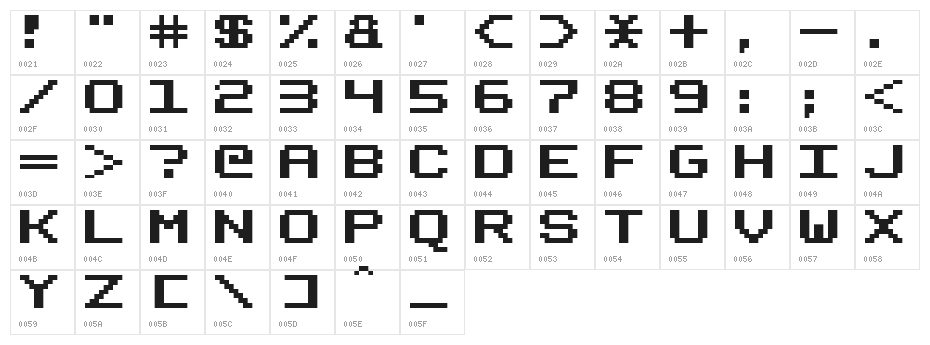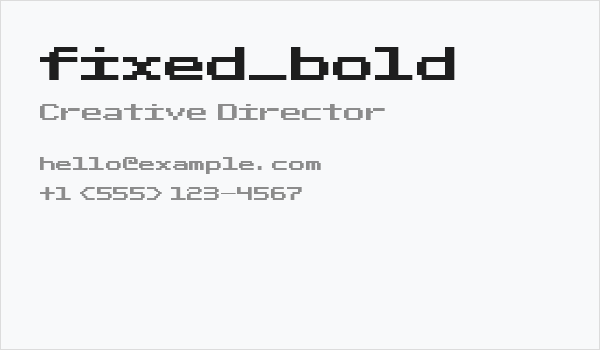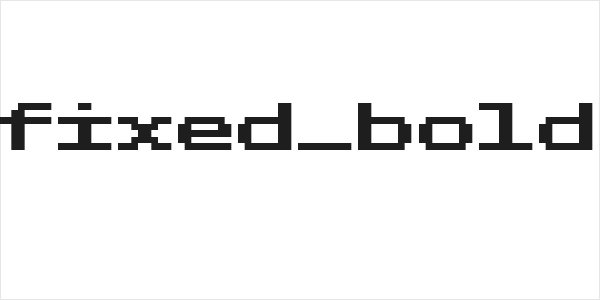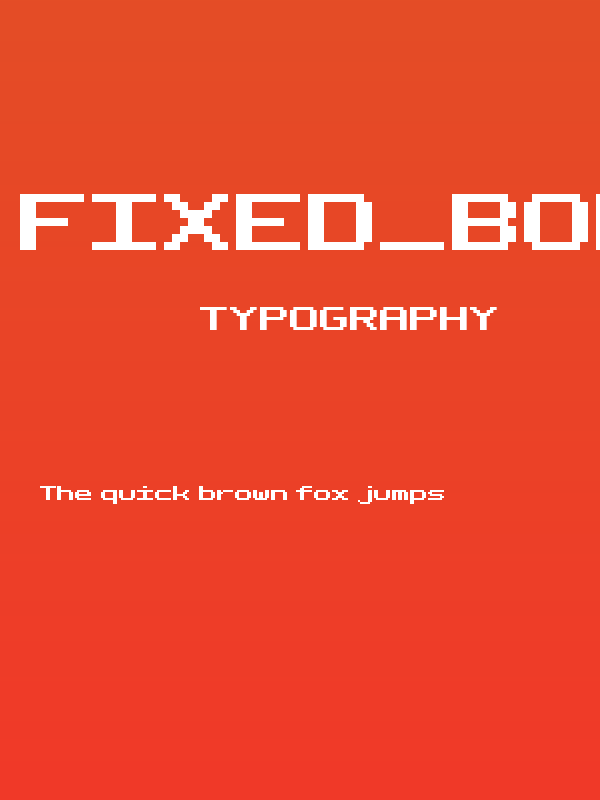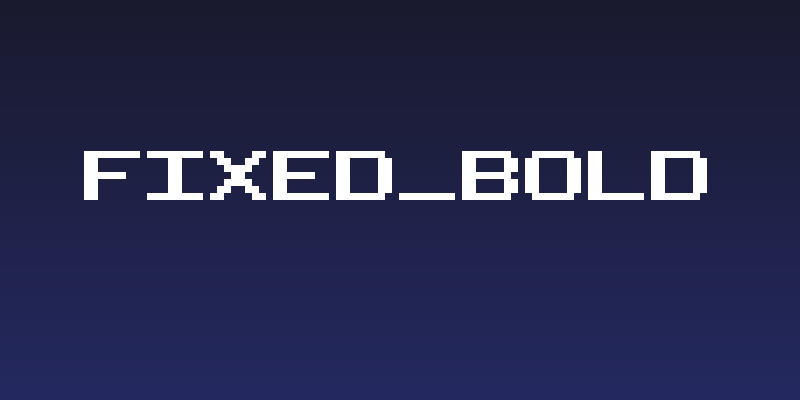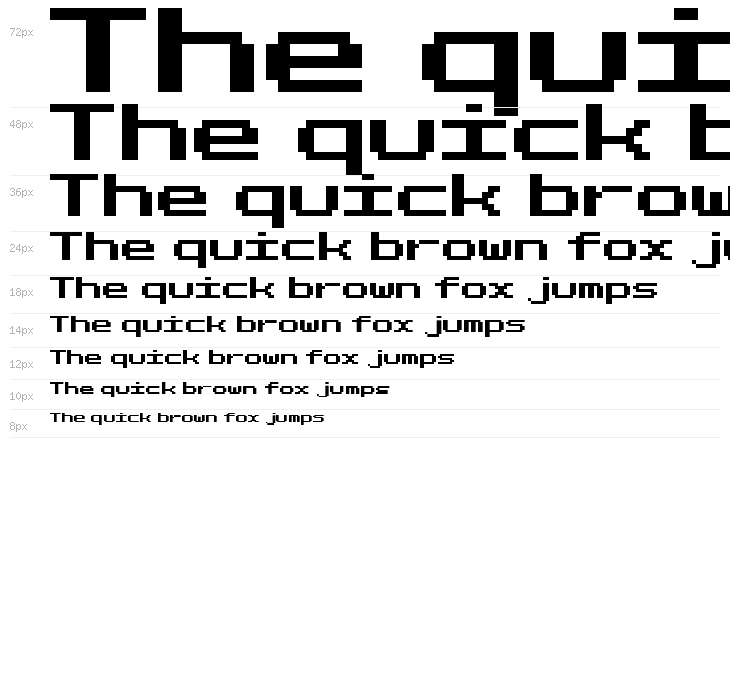
fixed_bold Font
| Categorie | Pixel |
| Stile generale | Retro |
| Caso d'uso | Logos, Digital displays, Video game text |
| Progetti proposti | Ideal for retro video games, tech-themed designs, digital art projects, and nostalgic branding. |